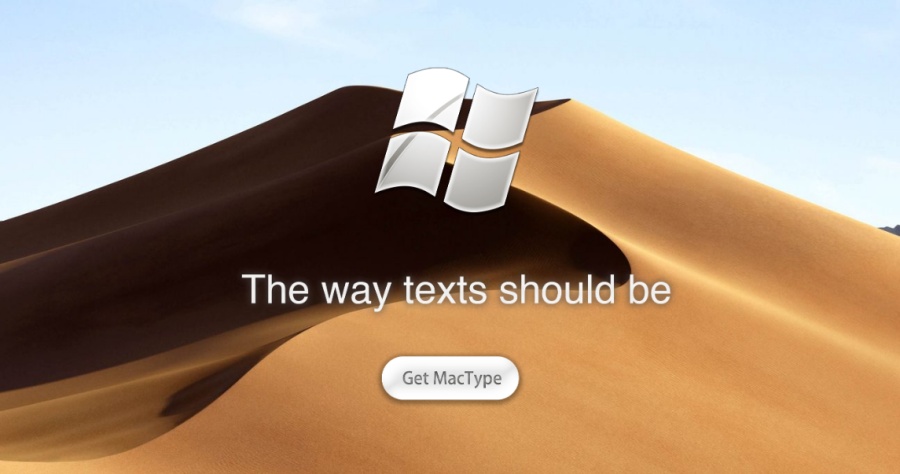
Windows 10 字型美化技巧,MacType 提升整體文字的舒適度
很多人用過 Mac 會回不去,是因為 Mac 文字的顯示讓人感到舒適,那在 Windows 上該如何仿 Mac 的文字體驗呢?大多人都會選擇使用 MacType 讓 Windows 仿 Mac 字體,Mac 的預設字是儷黑體,Windows 10 是中黑體,安裝 MacType 只需要不到 1 分鐘的時間,就可以讓 Windows 10 文字更好閱讀,若你也對 Mac 文字舒適度念念不忘的話,下載來安裝看看吧!
如果你是用 Windows 10 卻想用 Mac 字體怎麼辦 ? 就讓 MacType 來幫助你吧 !
大家可以看一下更換後的差異,左邊是原本 Windows 10 字體,比較淡且細,右邊是用 MacType 修改好字體,可以看到比較粗比較清楚,看了是不是很舒服呢 ! 以上就是 MacType 的操作介紹,是不是把字體變的更清楚了呢 ? 想把 Windows 10 轉換成 Mac 字體或是其他字體的朋友,可以試用看看 MacType 工具喲!